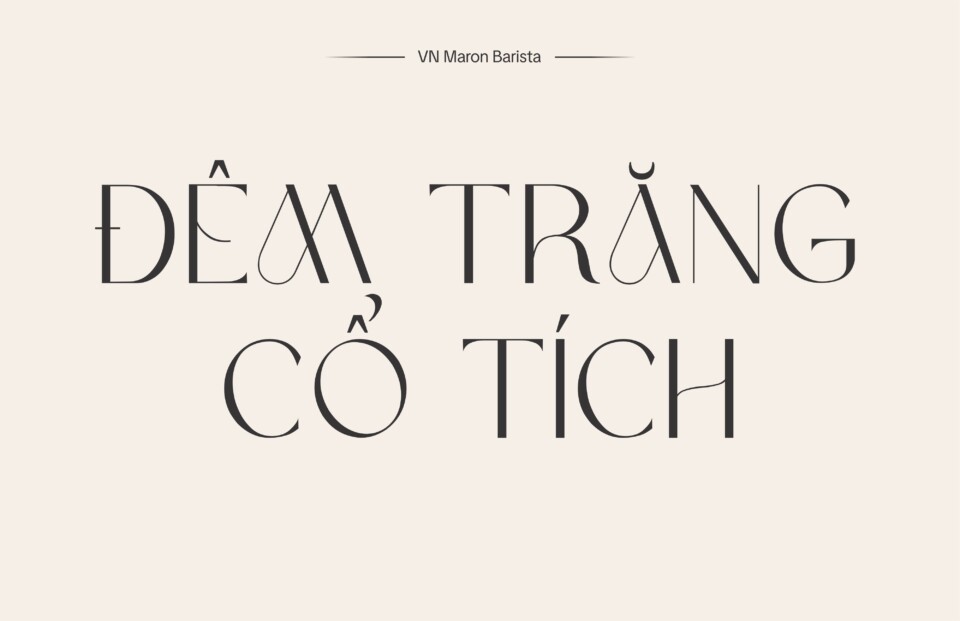
Font Việt hóa VN Maron Barista
Font Việt hóa VN Maron Barista – Bộ Font Chữ Vintage Độc Đáo Cho Thiết Kế Thẩm Mỹ
Giới thiệu về Font Việt hóa VN Maron Barista
Trong thế giới thiết kế đồ họa hiện đại, việc tìm kiếm một bộ Font Miễn Phí chất lượng và mang đậm dấu ấn cá nhân luôn là ưu tiên hàng đầu của các nhà sáng tạo. Font Việt hóa VN Maron Barista nổi lên như một sự lựa chọn hoàn hảo dành cho những ai yêu thích phong cách cổ điển, ấm cúng và tinh tế. Đây là bộ font chữ được lấy cảm hứng từ những tấm biển hiệu cà phê thủ công, mang đến cảm giác mộc mạc nhưng không kém phần sang trọng. Việc được việt hóa chỉn chu giúp người dùng tại Việt Nam dễ dàng ứng dụng vào các dự án truyền thông, trình bày bài giảng hay thiết kế các ấn phẩm văn hóa mà không lo lỗi font hay thiếu dấu tiếng Việt.
Những đặc điểm nổi bật của Font Việt hóa VN Maron Barista
Phong cách thiết kế đặc trưng
Font Việt hóa VN Maron Barista sở hữu những đường nét thanh mảnh kết hợp với các góc bo tròn mềm mại. Điểm mạnh của bộ font này chính là sự cân bằng giữa tính nghệ thuật và khả năng đọc hiểu. Dù bạn sử dụng cho các tiêu đề lớn hay các đoạn văn ngắn, font chữ này vẫn đảm bảo được sự rõ ràng. Đối với các bạn học sinh và giáo viên, việc sử dụng bộ font này trong các bài thuyết trình PowerPoint sẽ giúp nội dung trở nên lôi cuốn và chuyên nghiệp hơn rất nhiều. Kiểu dáng chữ mang hơi hướng hoài cổ của những thập niên trước tạo nên một không gian thị giác vô cùng thư giãn cho người xem.
Tính ứng dụng linh hoạt trong đời sống
Không chỉ giới hạn trong ngành quảng cáo, Font Việt hóa VN Maron Barista còn cực kỳ hữu dụng trong việc thiết kế thiệp mời, nhãn dán thủ công hoặc trang trí báo tường tại trường học. Với các bạn trẻ đang tập tành làm sáng tạo nội dung trên mạng xã hội, bộ font này sẽ là công cụ đắc lực để tạo nên những bức ảnh trích dẫn (quote) đầy cảm xúc. Nhờ cấu trúc ký tự được việt hóa hoàn chỉnh, mọi thanh dấu đều được đặt ở vị trí thẩm mỹ nhất, giúp văn bản tiếng Việt giữ được vẻ đẹp tự nhiên vốn có của nó.
Tại sao bạn nên sở hữu Font Việt hóa VN Maron Barista ngay hôm nay?
Tiết kiệm thời gian và tối ưu hiệu quả
Xây dựng phong cách cá nhân ấn tượng
Việc lựa chọn một font chữ phù hợp cũng giống như chọn một bộ trang phục đẹp. Với Font Việt hóa VN Maron Barista, sản phẩm của bạn sẽ có một “bản sắc” riêng biệt, khó nhầm lẫn với những font chữ hệ thống nhàm chán. Đây là cách tuyệt vời để các bạn học sinh ghi điểm trong mắt thầy cô qua những bài tập dự án sáng tạo. Một phông chữ đẹp không chỉ thể hiện sự tôn trọng người xem mà còn bộc lộ tư duy thẩm mỹ hiện đại của người sử dụng.
Kết luận về bộ Font Việt hóa VN Maron Barista
Có thể khẳng định rằng Font Việt hóa VN Maron Barista là một tài nguyên quý giá trong kho tàng phông chữ tiếng Việt hiện nay. Với sự kết hợp tuyệt vời giữa tính thẩm mỹ vintage và công năng sử dụng vượt trội, bộ font này xứng đáng có mặt trong thư mục cài đặt của bất kỳ ai đam mê thiết kế. Hãy bắt đầu thay đổi diện mạo cho các tác phẩm của mình bằng cách tìm kiếm và tải về Font Miễn Phí, Font Việt Hóa, Font Việt hóa VN Maron Barista để trải nghiệm sự khác biệt mà nó mang lại cho không gian sáng tạo của bạn ngay từ hôm nay.